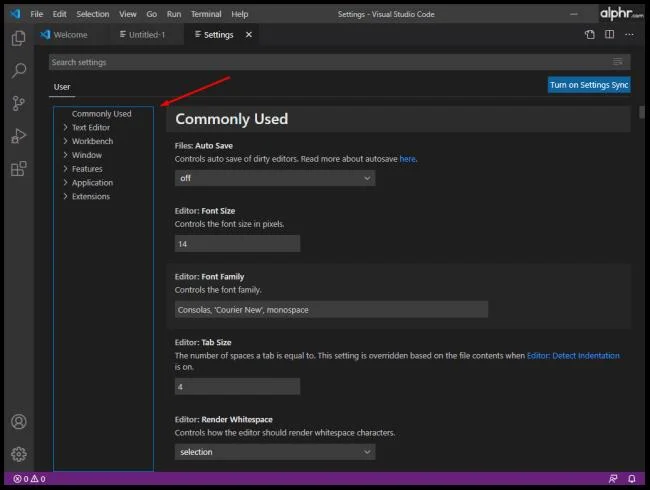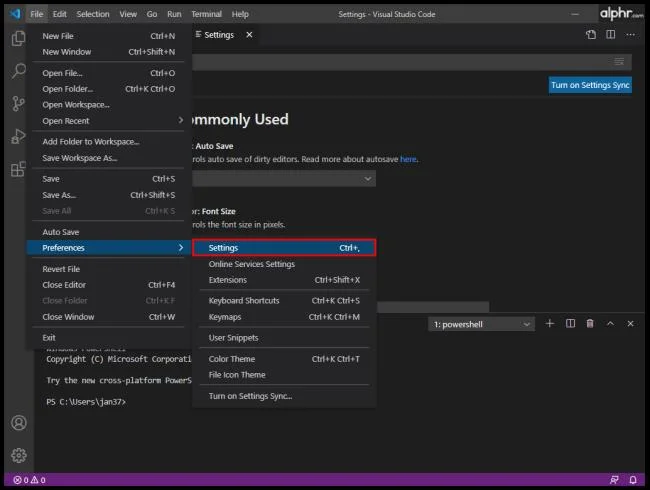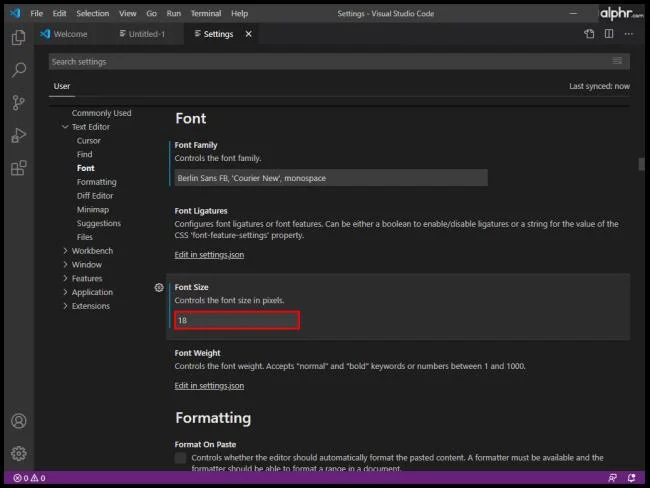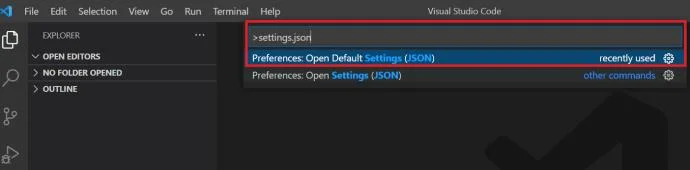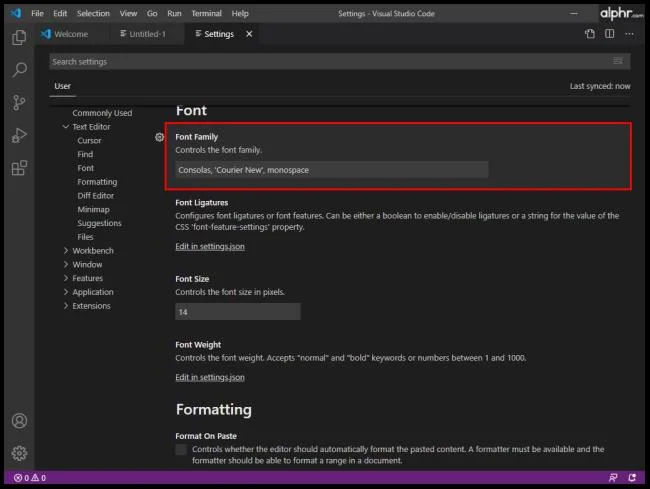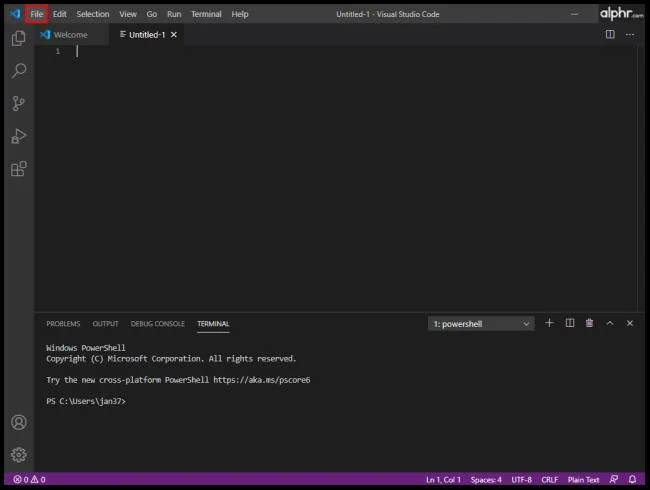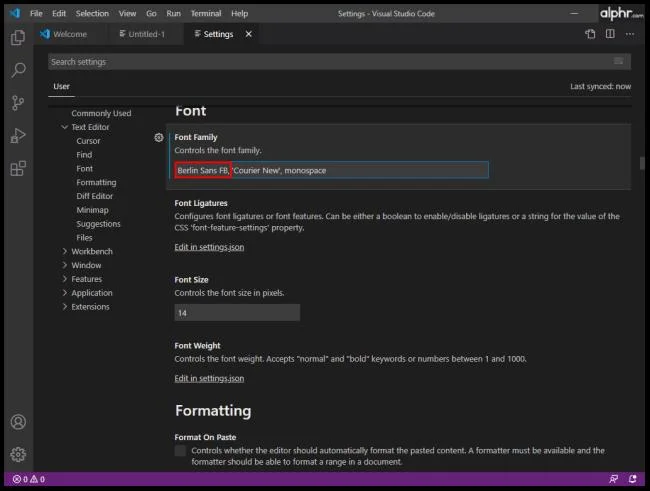
Лесно е за разработчика да подцени важността на своята работна среда. Не, ние не обсъждаме вашия стол, бюро или цвят на стената. Говорим за вашата виртуална работна среда.
Да накарате вашия редактор на код на Visual Studio да се чувства като у дома си е от съществено значение за ефективността на работата. Шрифтът покрива голяма част от цялостното VS усещане. В тази статия ще ви научим как да редактирате шрифтове в различни части на редактора на VS Code.
Причини за промяна на шрифта във VS Code
Дори ако сте разработчик, работещ с VS от дълго време, може да не знаете, че има опции за промяна на шрифта.
Ако не ви интересува защо изборът на вашия шрифт е важен, преминете направо към урока няколко параграфа по-долу. Не забравяйте обаче, че причините за промяна на вашия шрифт (посочени по-долу) могат да помогнат за вашето решение.
Защо шрифтовете са толкова важни във VS? Ако естетиката не е достатъчна за вас (и повярвайте ни, след часове и часове, прекарани в редактор на код, тя започва да има значение), става дума и за функционалност. И така, какво прави един шрифт „подходящ“ за VS?
На първо място, ще искате разликата между подобни герои да бъде забележима. Например разграничаването на числото „1“ от „l“ (малка буква L) може значително да ускори вашето кодиране и да ви спести време.
След това има факта, че някои разработчици обичат да използват лигатури. Лигатурите са няколко символа, свързани заедно, обикновено наричани „глифове“. Това може да означава много неща при кодирането.
Как да промените семейството на шрифтовете във VS Code
Без повече шум, ето как да промените семейството на шрифта във VS:
- Отворете VS редактора.
- Придвижете се до горната част на екрана и изберете „Файл“.
- Сега в падащото меню отидете на „Предпочитания > Настройки“.
- Сега ще видите секцията „Често използвани“ с меню от дясната страна на екрана. Ако се появи, можете да отворите и промените „Семейство шрифтове“ от тази страница или да продължите със стъпките по-долу.
- Щракнете върху „Текстов редактор > Шрифт“ и потърсете записа по подразбиране „Consolas, „Courier New“, monospace“.
- След това вместо „Consolas…“ въведете името на предпочитания от вас шрифт.
Това трябва автоматично да промени фамилията шрифтове.
Как да промените размера на шрифта във VS Code
Дори ако имате перфектно зрение, ще искате да поддържате очите си възможно най-удобни, когато пишете редове код. Несъответствията между подобни знаци са от съществено значение при избора на семейство шрифтове. Използването на подходящ размер на шрифта за кодиране обаче може да улесни очите ви и да ви помогне да работите по-ефективно.
Няма магическа формула за определяне на най-добрия размер на шрифта за кодиране. В идеалния случай ще искате да виждате знаците възможно най-ясно, но също така ще ви е необходима линията, за да пасне на VS прозореца. Така че, опитайте различни размери на шрифта и намерете идеалния, който отговаря на вашите нужди за кодиране.
Ето как да промените размера на шрифта във VS Code:
- Отидете до „Файл -> Предпочитания -> Настройки“.
- Потърсете секцията „Размер на шрифта“ и въведете предпочитания от вас размер на шрифта.
Как да промените шрифта на Explorer във VS Code
Функцията Explorer във VS Code работи като други файлови браузъри в повечето други приложения. Използва се за управление, разглеждане и отваряне на файлове и папки за работа по вашия проект. Тъй като VS кодирането се основава на папки и файлове, VS Code Explorer улеснява стартирането на вашия проект. Всичко, което правите, е да отворите файла/папката с помощта на VS Code. Толкова е просто.
Можете да очаквате да използвате VS Code Explorer до голяма степен. Ако размерът на шрифта на Explorer не ви устройва, ще се радвате да знаете, че можете да го промените.
- Отидете на „Файл -> Предпочитания -> Настройки“.
- Намерете секцията „Размер на шрифта“ и променете размера, за да отговаря на вашите нужди.
Как да промените стила на шрифта на терминала във VS Code
Вместо да превключвате прозорци или да променяте състоянието на съществуващия терминал, VS Code ви позволява да използвате интегриран терминал, намиращ се в корена на вашия проект/работно пространство. Разбира се, може да искате да промените шрифта за по-лесно използване. Ето как да промените шрифта на VS Code Terminal:
Промяна на опциите за шрифт във VS Code
Работата с опциите за шрифтове във VS Code не е толкова лесна, колкото промяната на шрифтове в програма за текстов редактор. Въпреки това, като се има предвид, че тук говорим за софтуер за кодиране, VS предлага голямо разнообразие от опции в сравнение с конкуренцията. Следвайте инструкциите в тази статия и направете своето изживяване с кодиране възможно най-персонализирано, удобно за потребителя и гладко.